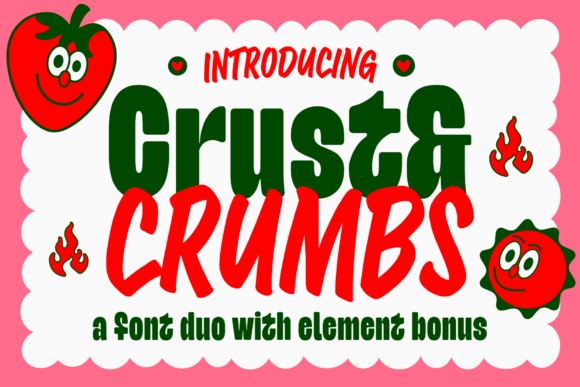
Crust and Crumbs
適切なデザイン要素を見つけるのは難しい場合がありますが、Crust and Crumbsは作品を即座に引き立てる優れたコレクションを提供します。
POD(オンデマンド印刷)製品、結婚式の招待状、またはソーシャルメディアのグラフィックを作成している場合でも、Crust and Crumbsは理想的です。